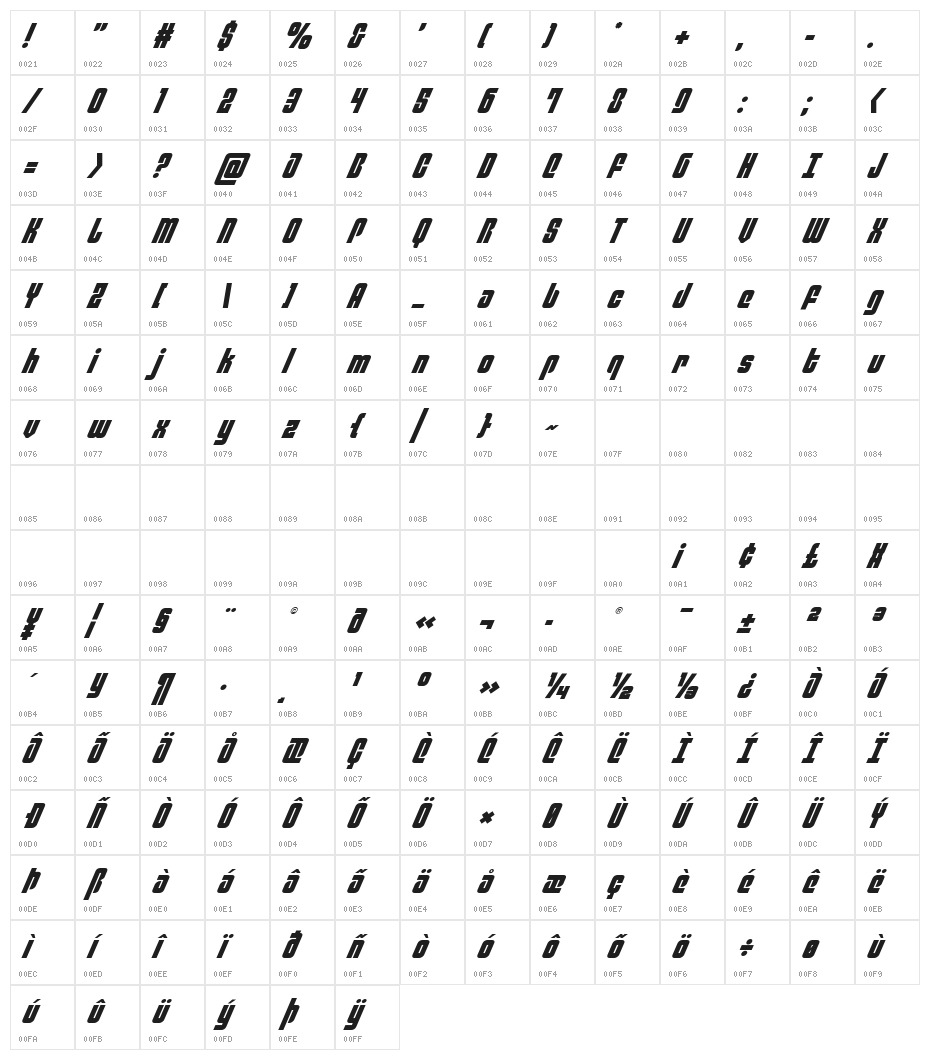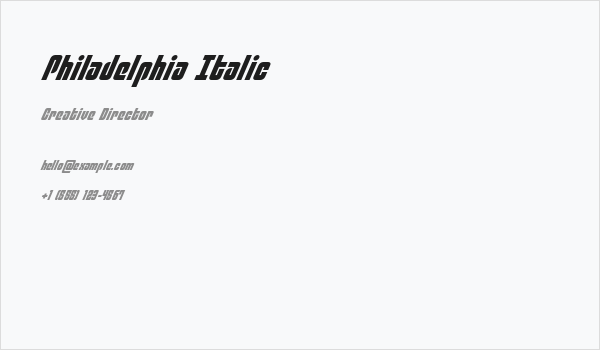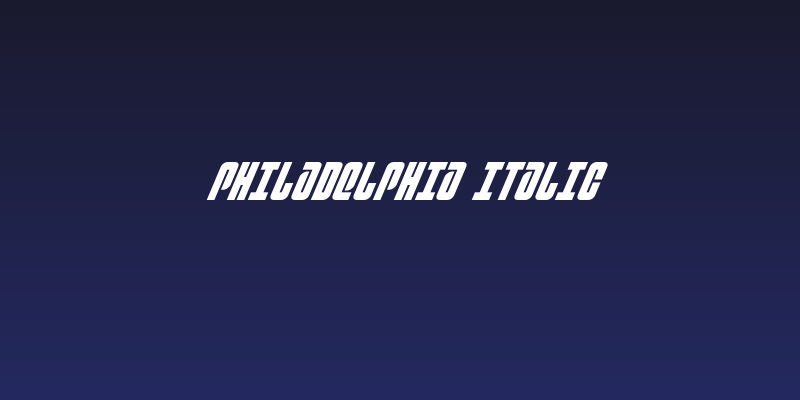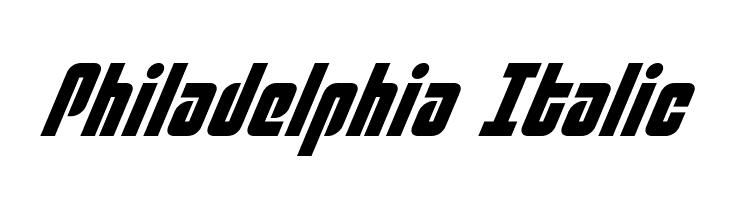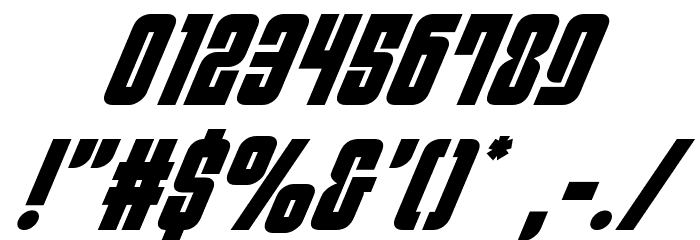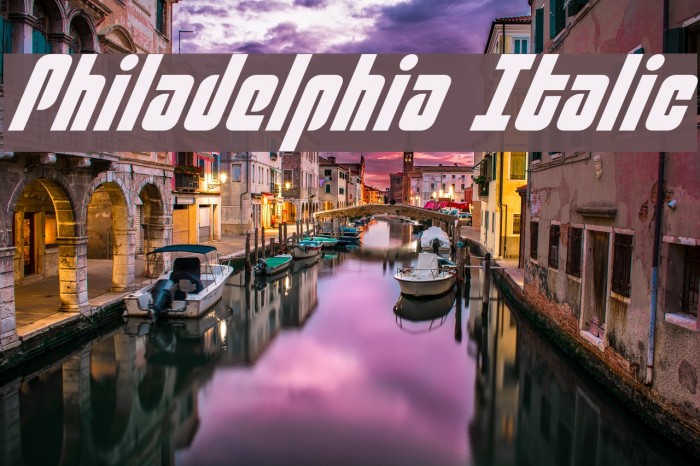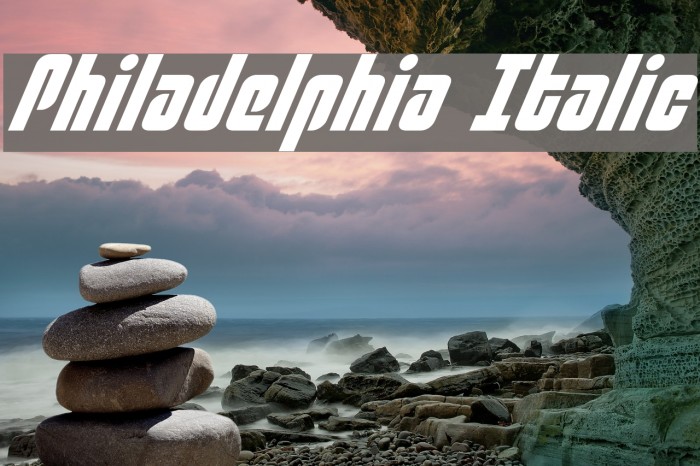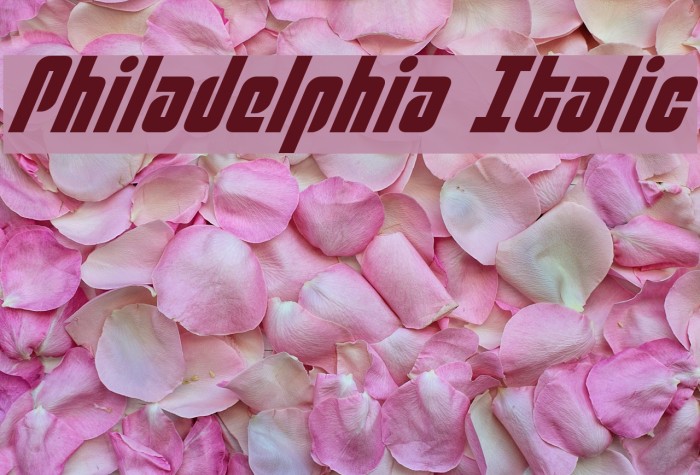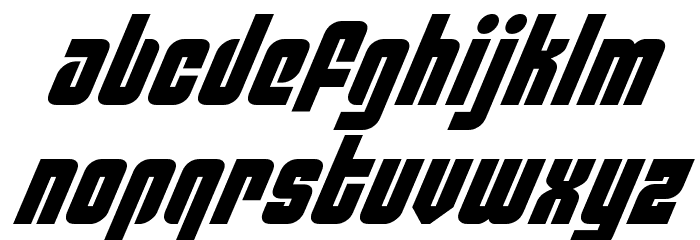
Philadelphia Italic Font
| Projets proposés | Ideal for sports branding, dynamic posters, modern advertisements, and any project needing a bold, energetic typeface. |